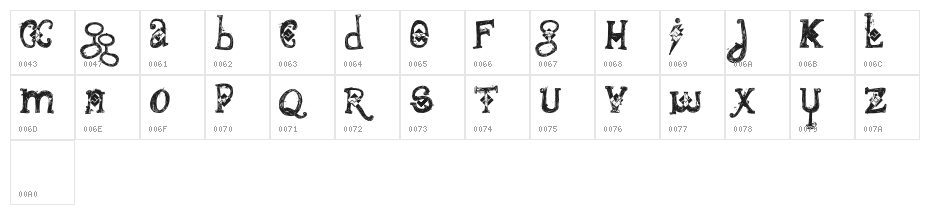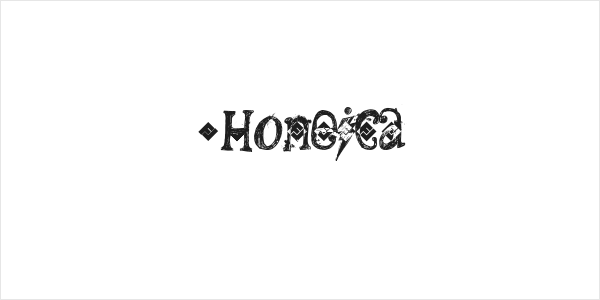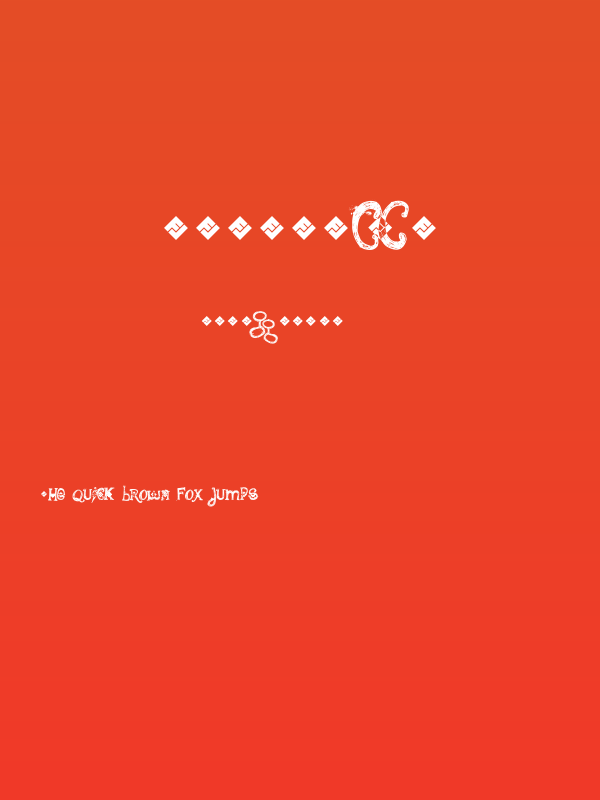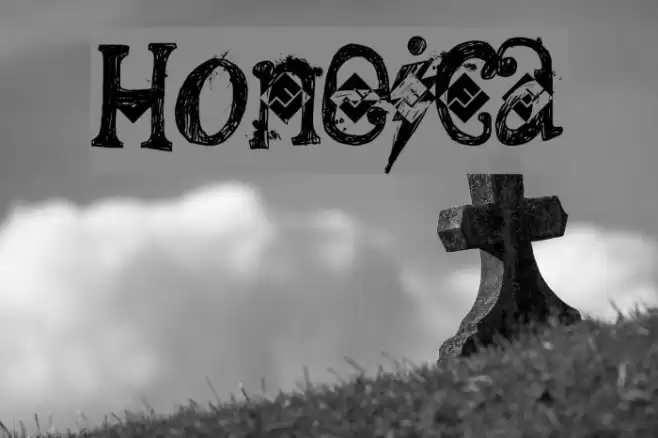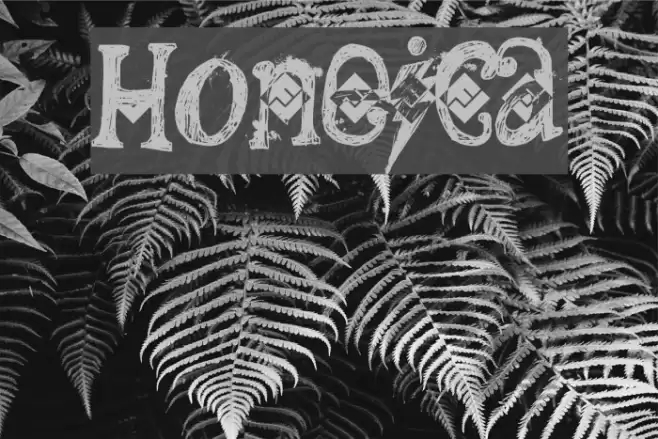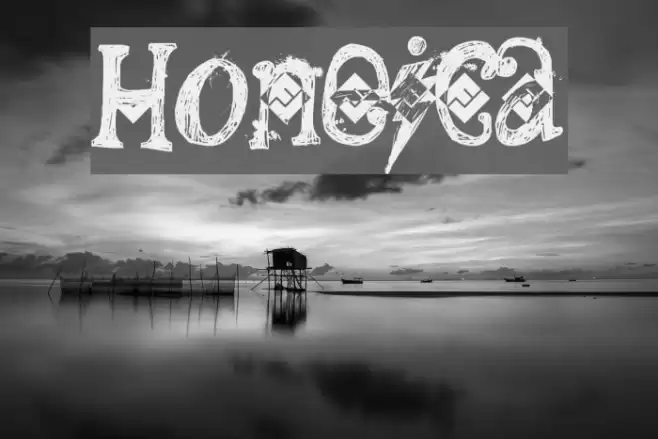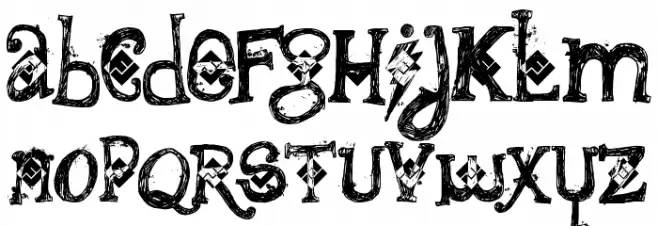
Shoneica Font
| Общий стиль | Grunge, Urban, Edgy |
| Рекомендуемые проекты | Album covers, posters, streetwear branding, skateboarding graphics, and edgy event flyers. |